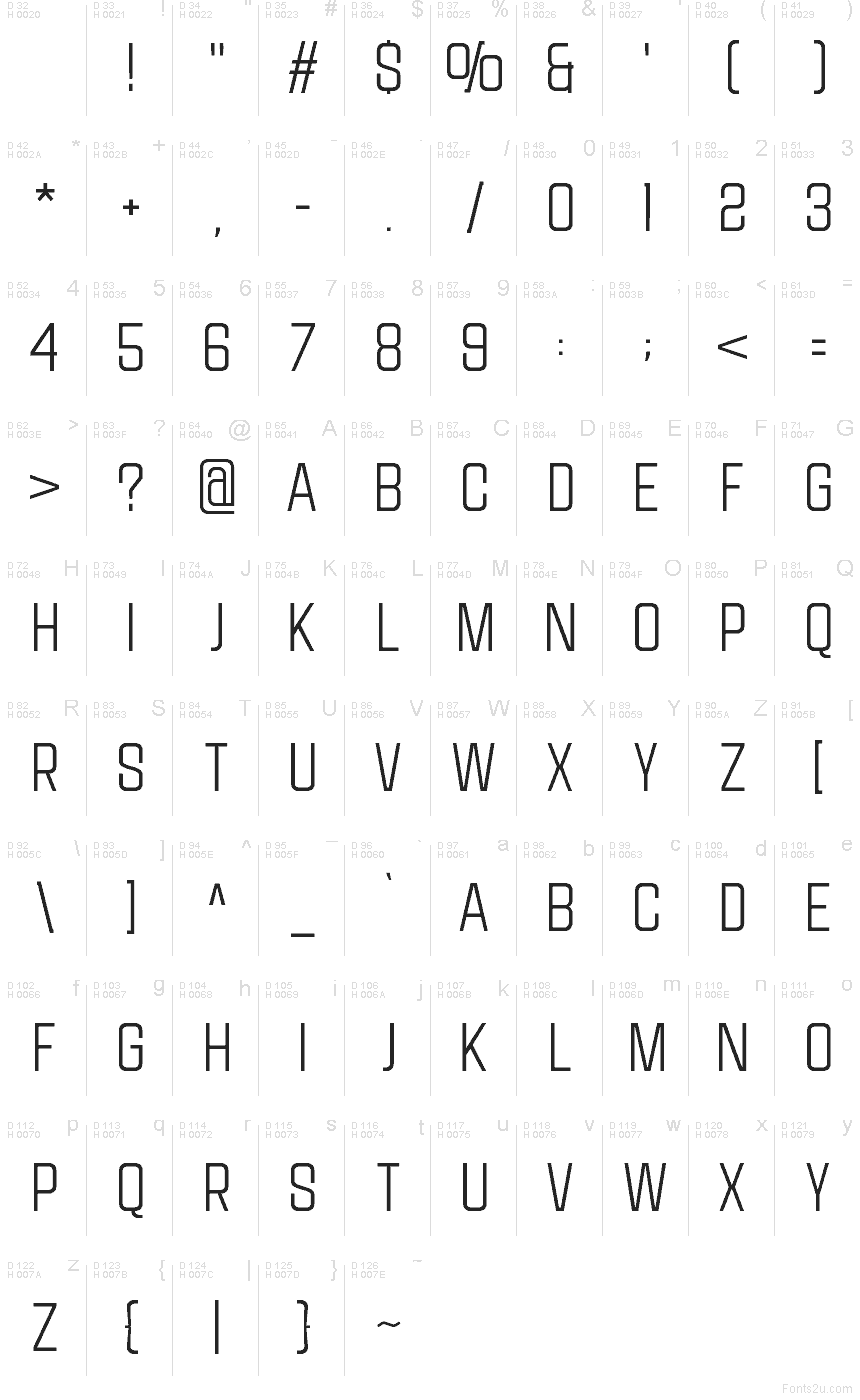
Analogo de Ari Juanda est une police sans-serif géométrique condensée et gratuite, dotée de capitales hautes et épurées. Ses traits fins et réguliers forment des lettres aux sommets aigus et un O rectangulaire aux coins arrondis. Ses proportions étroites confèrent aux caractères un aspect élégant et technique.
L'identité visuelle est son domaine de prédilection, en particulier pour les marques de mode ou les agences d'architecture recherchant un logotype épuré. Le packaging peut exploiter cette même structure verticale pour suggérer la précision sans paraître industriel. Les affiches et les couvertures de magazines conviennent également à sa silhouette allongée, qui peut faire écho à des lignes verticales, des façades de bâtiments ou des photographies aux cadrages serrés.